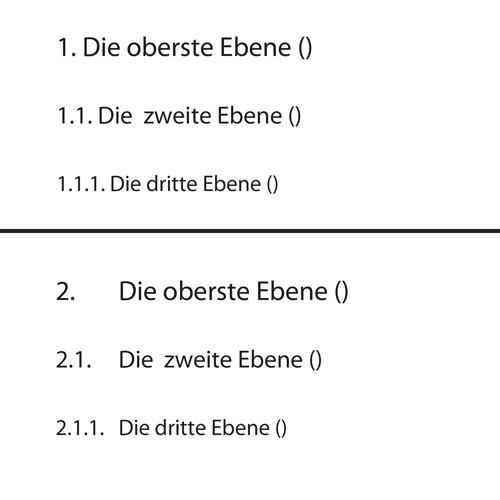
Entscheidungshilfe Typografie-Abschlussarbeit
ab Mitte April muss ich mit einer geisteswissenschaftlichen Abschlussarbeit (ca. 80 Seiten) beginnen, für die ich ca. 5 Monate Zeit habe. Im Vorfeld möchte ich - solange ich noch nicht in den Mühlen des Zeitdrucks zerrieben werde - schonmal die Formalitäten, vor allem die Schriftarten, festlegen.
Vorgegeben ist für den Fließtext Times New Roman oder eine ähnliche Schriftart, 12 pt Blocksatz und 1,5-zeilig. Fußnoten dito mit 10 pt, aber einzeilig. Ansonsten keine Anforderungen an die Schriftarten.
Bisher hab' ich in jeder Arbeit die Standardschriftarten Arial oder Times New Roman benutzt. Bis ich merkte, dass es sich dabei nicht gerade um die schönsten Schriftarten handelt. Ich bin schon ein ziemlicher Depp, das mir das erst jetzt aufgefallen ist und schäme mich dafür. Ab sofort soll daher ein neuer typographischer Abschnitt in meinem von graphischen Verfehlungen gezeichneten Leben beginnen.
Folgende Alternativen haben es bei meiner Schriftartsuche in die Mottoshows geschafft:
Überschriften:
• Futura
• Myriad Pro
• Franklin Gothic
Fließtext:
• Hoefler Text
• Minion Pro
• (Gentium)
Nun meine vielen Fragen:
I Welche Kombination würdet Ihr empfehlen?
II Ist es überhaupt üblich in den Geisteswissenschaften, für Überschrift und Fließtext zwei verschiedene Schriftarten zu benutzen (sofern nicht vorgegeben)? Habe da bisher noch nie darauf geachtet, vielleicht hat ja zufällig einer hier im Forum die typographische Entwicklung von Soziologie-, Geschichts-, Philosophiemagisterarbeiten/-dissertationen in letzter Zeit miterlebt und kann berichten?
III Welche Standards haben sich in der Typographen-Szene durchgesetzt (oder gibt es gar Grafik-DIN?) für folgende Formatvorlagen:
• Wie weit einrücken bei neuem Absatz (außer unmittelbar nach Überschrift)?
• Wievielt pt oder Zeilen Abstand von Überschrift Ebene 1 (Ü1) zum vorherigen Kapitel (Fließtext) bzw. zum folgenden Kapitel (Fließtext) oder aber zur folgenden Unterüberschrift (Ü2) - manchmal folgt nämlich auf eine Überschrift direkt die Unterüberschrift
• dito, aber für Ü2 und Ü3
• Typographische Absetzung der Überschriftenebenen: Welche Schriftgröße für Ü1, Ü2, Ü3 und Ü4 (werde wohl insgesamt 4 Überschriftenebenen verwenden)? Markierungen durch Fett- oder Kursivdruck möchte ich vermeiden. Die Überschriftenhierarchie soll allein durch unterschiedliche Schriftgrößen sowie unterschiedliche Abstände zu den umgebenden Textebenen ersichtlich sein - dezent, aber nicht unauffällig.
• Wie rechne ich 12 pt Times New Roman am besten in eine Schriftgröße einer anderen Schriftart um, so daß z.B. auf einer DIN A4-Seite genau so viele Wörter in der anderen Schrift und Schriftgröße Platz finden wie 12 pt TNR?
Zum Schluss noch ein paar weitere Angaben:
Auf jeden Fall benötige ich folgende Sonderzeichen: Č, Š, Ž, č, š, ž, ë und ė, da das Themengebiet höchstwahrscheinlich in Osteuropa liegen wird.
Fragen über Fragen also! Diesmal aber möchte ich die Arbeit auch typographisch überdenken und erfahrungsgemäß gilt: Je früher und je detaillierter mit der (auch typographischen) Planung anfangen, desto weniger Probleme kurz vor Abgabe. Daher meine detailversessenen Fragen.
Willkommen im Forum!
Mal so ganz spontan und ohne jetzt detailliert auf Deine Fragen einzugehen: hast Du Dir mal die Lido STF von Herrn Štorm angesehen? Die ist von der Times quasi abgeleitet, hat aber einen ziemlich eigenständigen Charakter. Und sie umfaßt mit Sicherheit die Zeichen, die Du brauchst. Wenn Arial und Times recht eingefahrene Schriftarten an der Fakultät sind, dann ist es u.U. gefährlich, sich zu weit davon wegzubewegen. Die Lido ist da ggf. ideal, da sie Times-ähnlich ist, aber trotzdem einen ganz eigenen Charakter hat.
Ansonsten im Vorfeld mit dem Dozenten/Professor klären, daß ein bestimmtes Layout in Ordnung geht. Das erspart Dir im Zweifelsfall daß Du kurzfristig noch tiefgreifende Änderungen vornehmen mußt.
Alternativ zu Christians Vorschlag wäre aber auch die Kombination Myriad/Minion eine gute Lösung, sofern die beiden Schriften alle von Dir benötigten Sonderzeichen an Bord haben. :-)
Servus :)
Aaalso, mal vorweg: Myriad und Minion sind eine schöne Kombination, wenn Du kein Budget für eine weitere Schrift hast :) Gibt es ja kostenlos, zumindest die wichtigeren Schnitte :)
Von der Furura und der Franklin würde ich bei sowas (Fließtext ohne irgendein Corporate Design, das diese Schriften sinnvoll vorgibt) ganz weiten Abstand nehmen: Beide sind relativ auffällig, speziell die Futura, die auch sehr inflationär und oft ganz falsch eingesetzt wird ...
Zum einen sind Ligaturen Gewohnheitssache. Bei Textsatz (LaTeX) bekommt man die automatisch und fast immer richtig geliefert. Die Trennmuster und deren lokale Anpassungen helfen dabei und der Nutzer hat fast keinen zusätzlichen Aufwand. Zum Anderen ist das auch eine Sache der Schriftgröße. Im normalen Fließtext fällt das Fehlen von Ligaturen nicht/kaum auf. Bei Überschriften kann das schon anders sein. Das ist aber auch abhängig von der Schrift. Je dekorativer desto kritischer, speziell bei extraordinären Serifen kann es zu Problemen kommen. Das sollte bei der Schriftwahl berücksichtigt werden, so man die Ligaturen nicht vom Programm frei Haus geliefert bekommt (LaTeX oder echte DTP-Weichware) oder sich den Aufwand für das manuelle Setzen antun will.